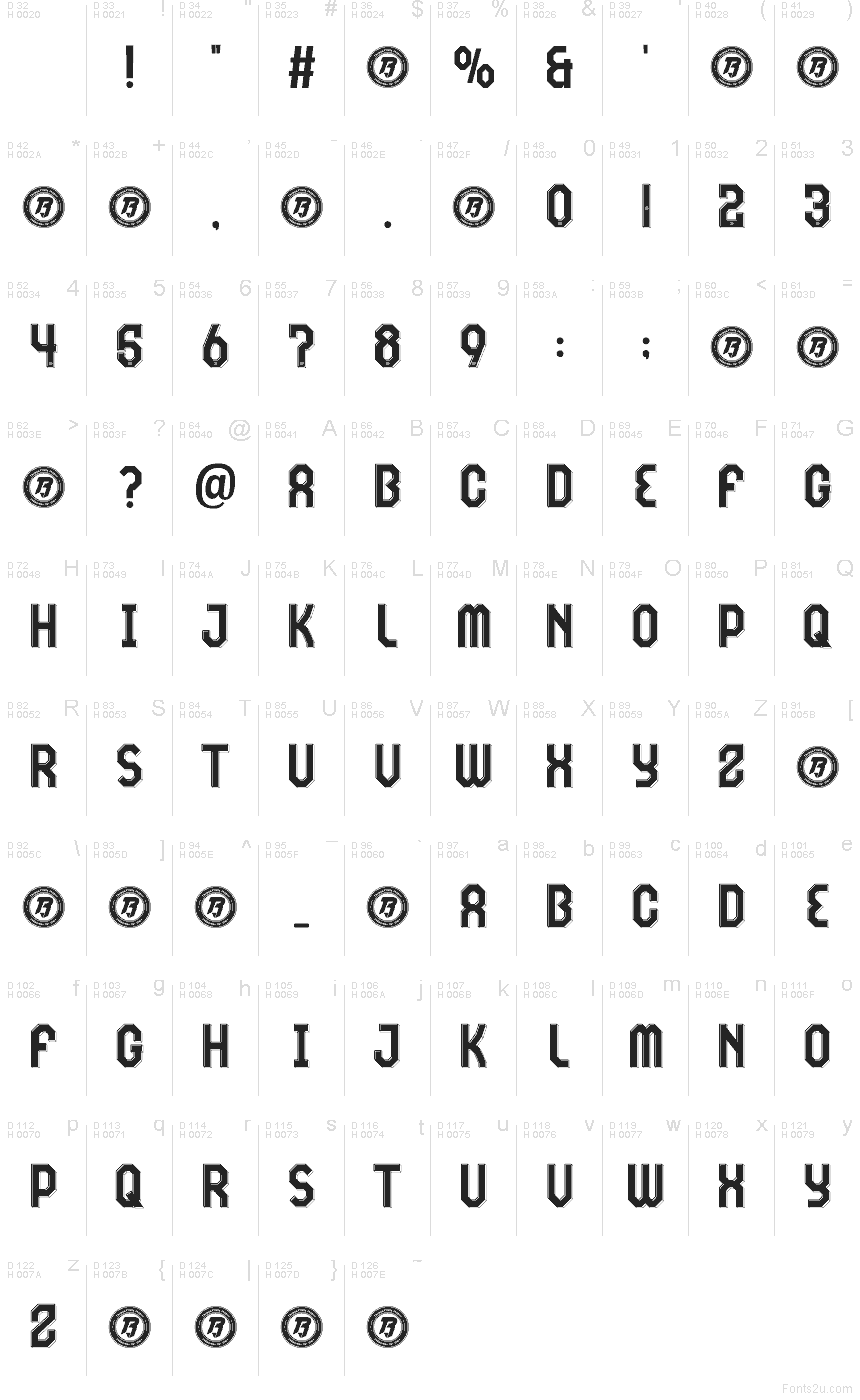
Feijenoord de Trequartista Studio es una tipografía display techno gratuita con letras octogonales rígidas, que evocan los emblemas deportivos y la señalética industrial. Sus mayúsculas destacan por las esquinas cuadradas, los chaflanes profundos y un contorno interior audaz, lo que le da a la fuente un aspecto compacto, mecánico y algo retro, sin perder su toque moderno.
Es ideal para titulares de pósteres, branding de esports, diseños de streetwear, portadas de álbumes y tarjetas de título donde busques un emblema sólido en lugar de letras neutras. Al ser una tipografía gratuita, también funciona muy bien para monogramas y textos cortos, ya que sus ángulos recortados y detalles internos hacen que incluso un par de letras parezcan una insignia hecha a medida.